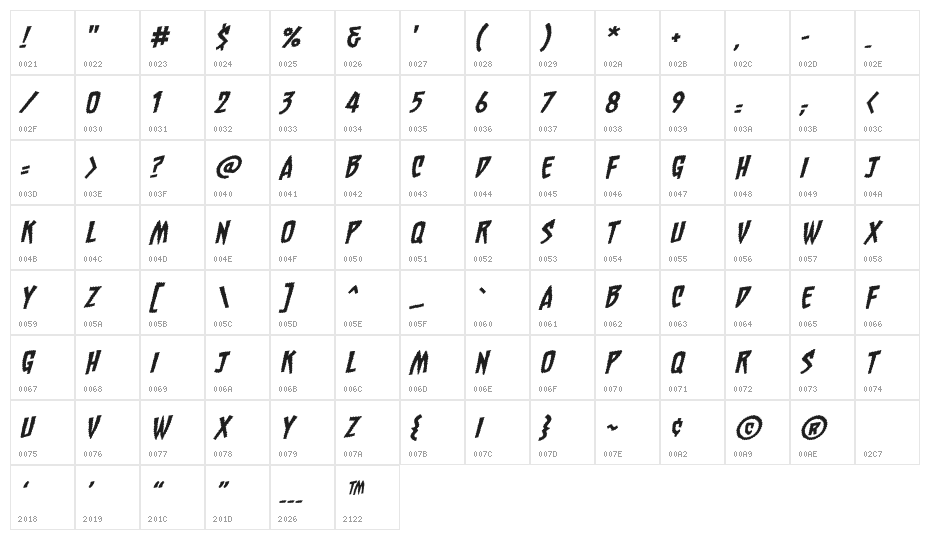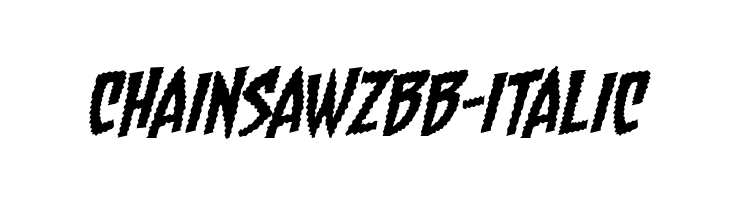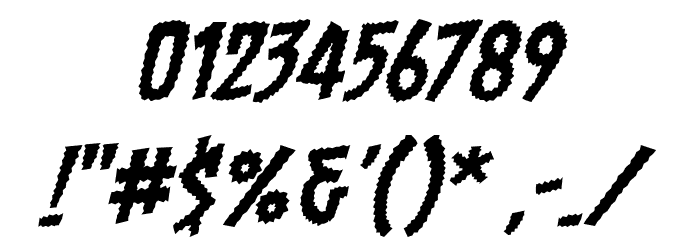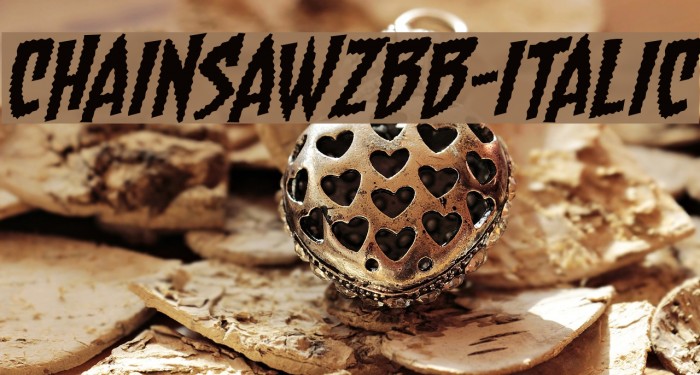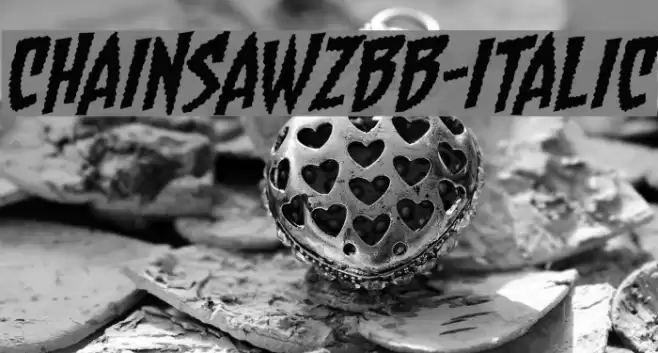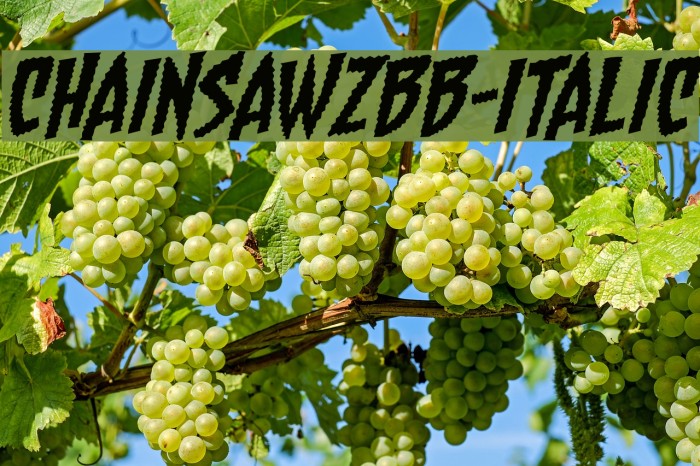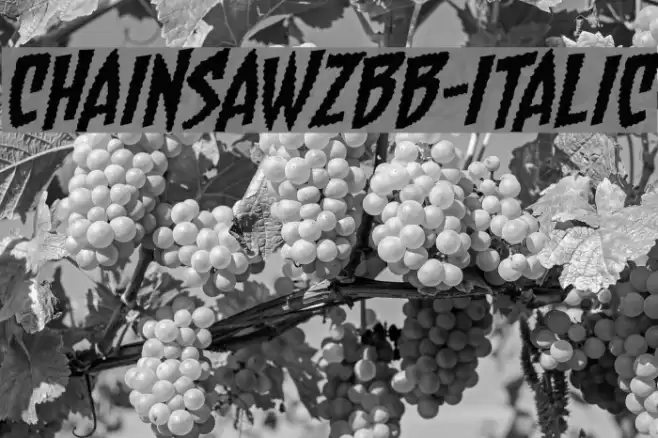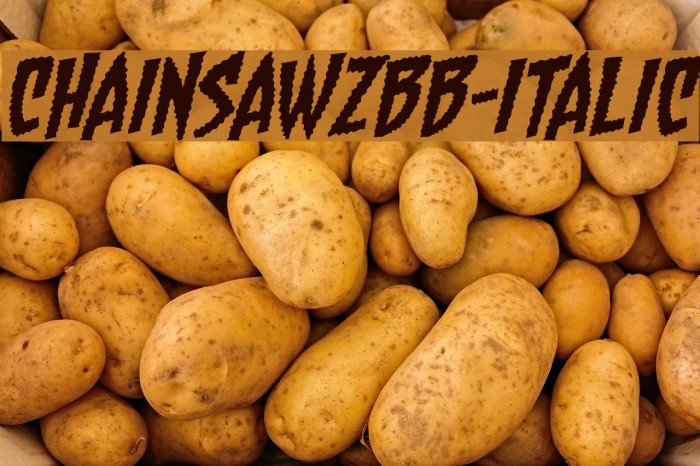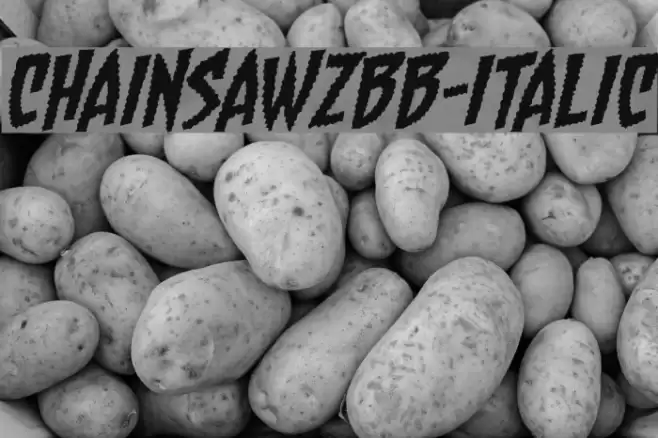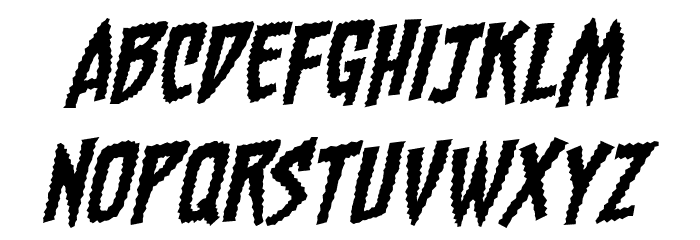
ChainsawzBB-Italic Font
| Projets proposés | Ideal for horror-themed designs, edgy posters, Halloween invitations, and any project needing a bold, rugged look. |